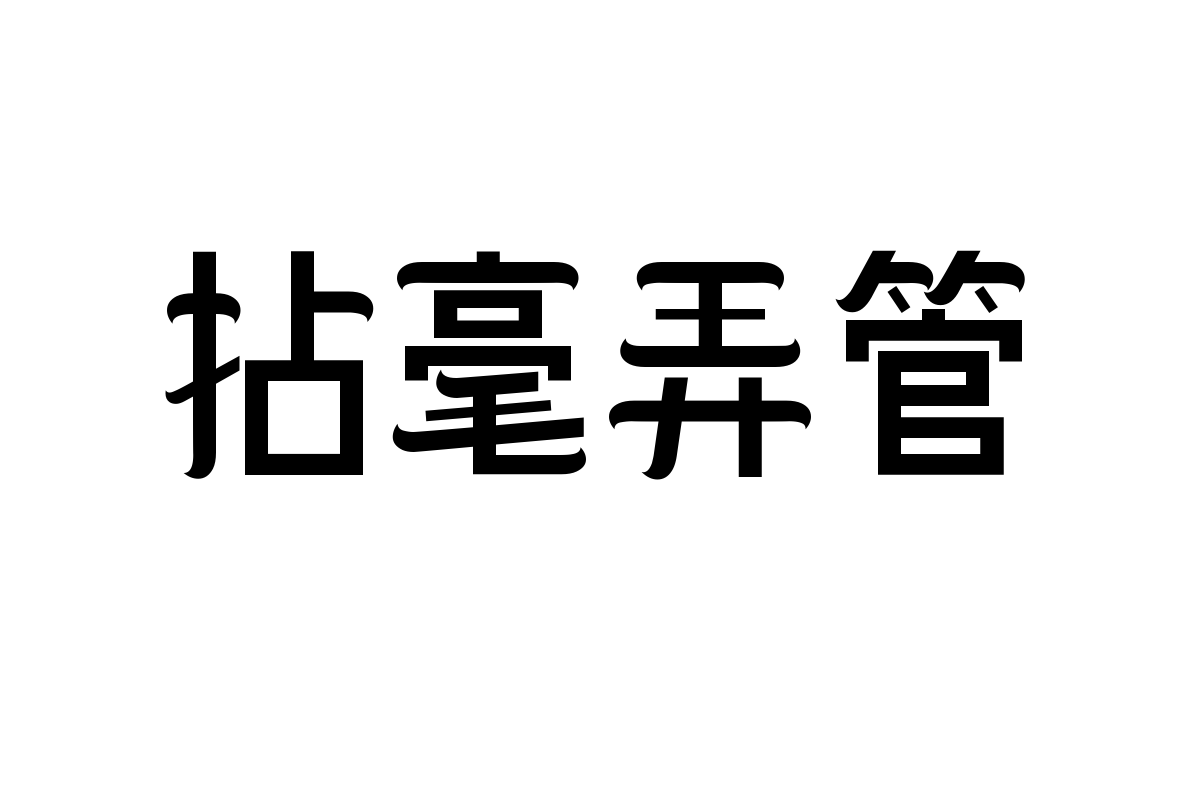
造字工房行舟体是一种具有独特风格的字体。它采用了简洁、流畅的线条,使得整个字体看起来既现代又具有艺术感。这种字体的特点是笔画粗细变化丰富,既有粗犷的线条,也有细密的笔画,给人一种强烈的视觉冲击力。同时,行舟体还注重平衡和对称,使得整个字体看起来既稳定又和谐。
造字工房行舟体适用于各种设计领域,如广告、包装、书籍等。它的应用范围非常广泛,无论是需要突出个性还是追求简洁明了的设计,都可以使用这种字体来达到目的。此外,由于行舟体的独特风格,它也常常被用于个性化定制和创意设计中,为设计师提供了更多的灵感和选择。